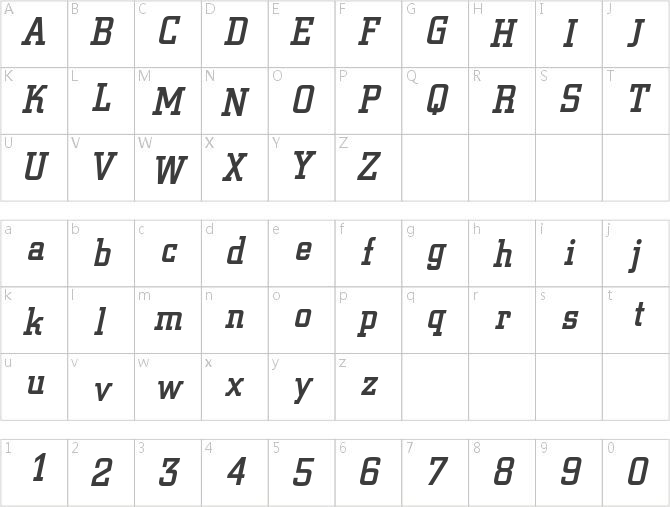
a_CityNova-Italic 詳情頁(yè)
a_CityNova-Italic字體字庫(kù)是一款讓人賞心悅目、百看不厭的英文字體,適合各類廣告和產(chǎn)品包裝設(shè)計(jì)應(yīng)用,字體大小0.05MB,格式為ttf字體,上傳用戶是黃肖,作者/版權(quán)方為未知